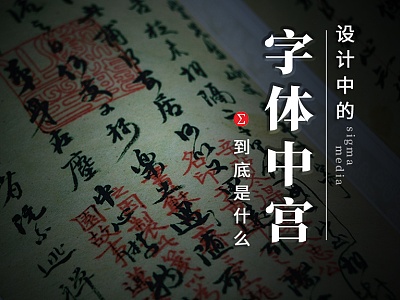
设计中的中宫指什么?不懂这个谈字体结构和造型都白搭
字体设计中,新手设计师才说字体结构松散或紧凑,设计老司机只谈中宫。
你肯定也有这样的感受,因为谈论字体结构松散或紧凑只是对字体造型的直观描述,并无更多内涵或实际意义上的指导。
那中宫到底有何不同?又怎样影响着字体结构和造型?看到最后你就会恍然大悟了!
一、深扒字体设计之中宫的来龙去脉
中宫的概念源于书法,写书法时常以不同的“界格”做参考,从而确定每个笔画的位置,临摹字帖时也常用“界格”做参考,以确定临摹字的笔画和原贴字笔画在同一个位置。
常见的田字格、米字格、回宫格、九宫格等等就是不同的界格。
写楷书常参考的界格是“九宫格”,所谓九宫,就是把一个大方格再等分成九个小方格,上下的三格三格分别称“上三宫”“下三宫”,左右两格分别称“左宫”和“右宫”,而最中间的一格就是中宫。
如你所做,楷书的特点是把所有笔画有序的靠拢、凝聚在字的中心,也即中宫,所以有“中宫收紧”的说法。
《晋唐小楷八种》
因为楷书被称为汉字的标准字,代表了标准的汉字结构造型,所以中宫的概念也就被设计所借鉴。
《隋苏慈墓志》
字体设计中所说的“中宫”也是指九宫最中间的那一格,粗暴理解就是汉字重心周围的区域,我们通过衡量这个区域笔画的位置、布局来分析汉字的结构和造型。
二、字体设计之中宫是汉字的特色主义
很多小伙伴可能听说过字谷、字怀等概念,那这些说法和中宫是一回事吗?有什么异同?
字谷的概念来自西文字母设计,字谷指字母中部分或完全封闭的空间,简单理解就是字母当中留白部分的面积。
而“字怀”的说法多见于日本字体设计相关书籍,指笔画间留白部分的多少。这种提法类似于国画中的留白,是对虚实空间探讨的一种说法。
中宫明显与二者有很大不同,比对三者概念就很容易明白,虽然处理字体中宫会考虑到汉字的留白,但中宫并不指留白,而是指字体笔画在重心区域的造型和布局,指的是实实在在的笔画结构。
可见,中宫是不受字重影响的,而字怀却会受到字重影响,字重大小会影响到笔画粗细,而笔画粗细自然就影响到笔画间留白也就是字怀的多少了。
So,中宫是汉字的特色主义,千万不要和字谷、字怀混淆了。
三、当设计师谈中宫时都在谈什么?
中宫虽然让人不明觉厉,但深扒了中宫的概念和字谷、字怀的不同后,小伙伴们应该也很容易理解。那字体的中宫怎样影响着字体?中宫具体又该如何处理?
设计师谈论中宫,其实着眼于字体重心周围的笔画布局来分析汉字间架结构的。
中宫对字体结构和造型的影响是关键性的,同一种字体都有着一致的中宫,也就是说中宫影响着字体的骨架,进而会影响到字面的大小。
我们用结构的松紧来描述字体中宫的不同,当然这种松紧也是可粗略测量的,字体笔画聚拢或靠近中宫框,就是字体中宫紧凑,反之,字体笔画分散或远离中宫框,就是字体中宫松散。
字体中宫松散就是内松外紧,这样的字体往往字面大,而字体中宫紧凑就是内紧外松,这样的字体当然是字面小啦!
这就是关于中宫的一切,现在是不是对它了解的一清二楚了?关于字体结构和造型的细节,掌握中宫让你平地起飞进阶老司机!